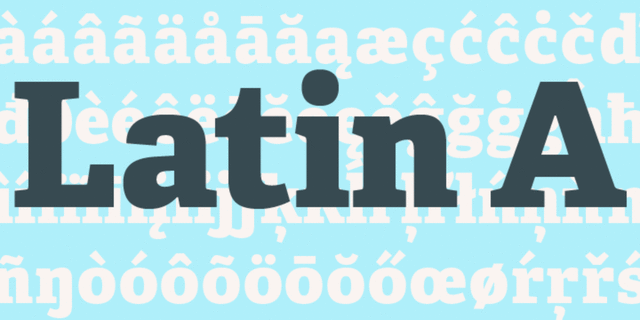
Adelle – это брусковая антиква, сделанная специально для интенсивного редакционного использования, в основном, в газетах и журналах, его характер и гибкость делают этот шрифт многоцелевым.
Большой диапазон жирности обеспечивает очень разборчивый и нейтральный вид при использовании в текстовых размерах, обеспечивая надежность, ожидаемую от газетного шрифта. Ненавязчивый характер позволяют этому шрифтовому семейству выглядеть безупречно в текстовой полосе, даже в самых требовательных изданиях.
При большем размере в печати, Adelle показывает свои особенности, благодаря которым этот шрифт легко запоминается. Гарнитура состоит из 14 начертаний, от тонких до сверхжирных, и содержит более 900 символов. Энергичный характер, так присущий брусковым шрифтам, становится очевидным, при использовании в заголовках и подзаголовках.
Набор символов включает в себя около 900 знаков, включая капитель, дроби, минускульные цифры, индексы, а также пиктограммы и стрелки. Adelle поддерживает более 40 языков, использующих расширенную латиницу и кириллицу.
Шрифт разработан Вероникой Буриан и Хосе Скаглионе и выпущен студией TypeTogether в 2009 году.